Fancy Textstile sind besondere Schriftarten (z. B. fett, kursiv oder dekorativ), die deine Texte visuell hervorheben und mehr Aufmerksamkeit erzeugen. Auf X (formerly Twitter) werden dafür keine echten Fonts genutzt, sondern Unicode-Zeichen, die wie stylische Schrift aussehen.
Einleitung
Auf X (formerly Twitter) spielt Text eine zentrale Rolle. Mit wenigen Worten musst du Aufmerksamkeit gewinnen und deine Botschaft klar vermitteln.
Im schnellen Feed entscheiden Sekunden darüber, ob ein Tweet gelesen wird oder untergeht. Auffällige und gut strukturierte Texte helfen dabei, den Scroll zu stoppen.
Stylische Texte können dein Engagement deutlich steigern. Sie machen Tweets visuell interessanter, heben wichtige Aussagen hervor und motivieren Nutzer zu Likes, Replies und Shares.
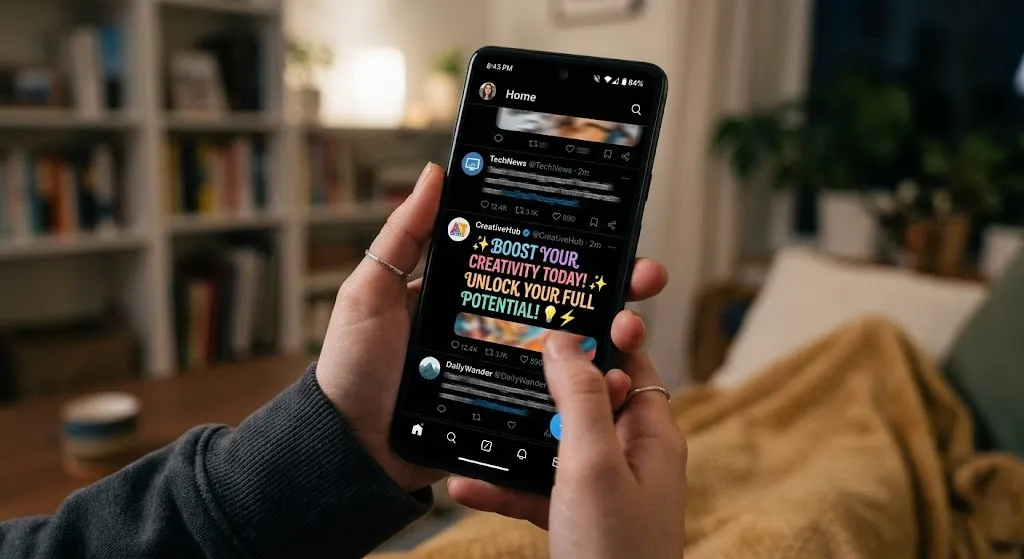
Warum Fancy Textstile auf Twitter/X wichtig sind
Fancy Textstile auf X (formerly Twitter) helfen dir, deine Tweets visuell hervorzuheben und mehr Aufmerksamkeit zu bekommen. In einem schnellen Feed machen kleine Unterschiede oft den größten Effekt.
Aufmerksamkeit & Scroll-Stop-Effekt
Im überfüllten Feed fallen stylische Texte sofort auf. Sie durchbrechen den normalen Textfluss und sorgen dafür, dass Nutzer beim Scrollen stoppen.
Engagement (Likes, Retweets, Replies)
Auffällige Texte machen deine Inhalte interessanter. Dadurch steigt die Wahrscheinlichkeit, dass Nutzer liken, kommentieren oder deinen Tweet teilen.
Persönliche Marke & Stil
Mit Fancy Text kannst du deinen eigenen Stil entwickeln. Das stärkt dein Branding und sorgt dafür, dass deine Tweets wiedererkannt werden.
Wie funktionieren Fancy Textstile technisch?
Fancy Textstile auf X (formerly Twitter) wirken wie besondere Schriftarten, sind aber technisch etwas anderes.
Unicode statt echte Fonts
Fancy Text ist keine echte Schriftart. Stattdessen werden normale Buchstaben durch Unicode-Zeichen ersetzt, die ähnlich aussehen (z. B. A → 𝓐, 𝔄, 🅰).
👉 Es handelt sich also um spezielle Symbole, nicht um Formatierung
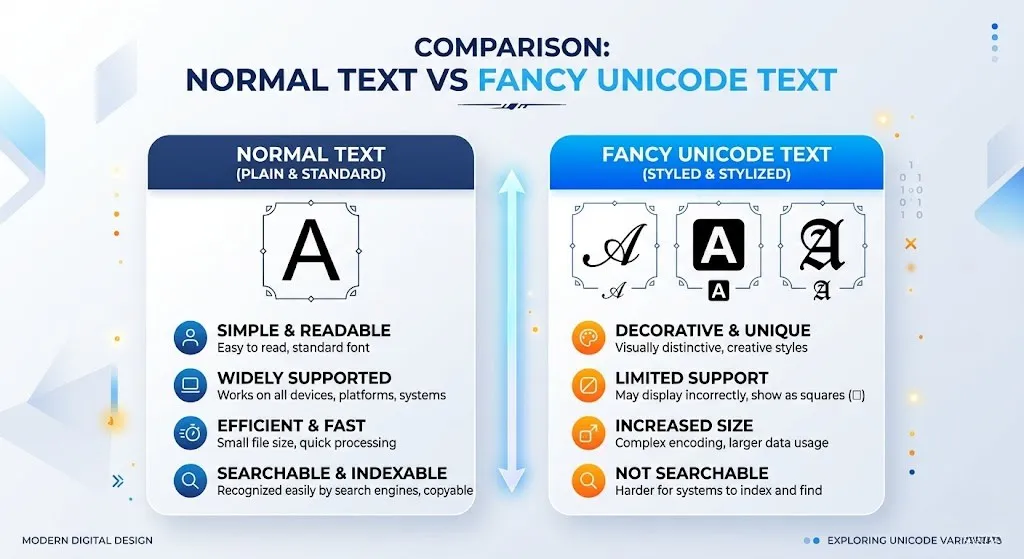
Copy & Paste Prinzip
Die Funktionsweise ist einfach:
- Text in einen Generator eingeben
- Stil auswählen
- Ergebnis kopieren
- In den Tweet einfügen
👉 Der Text bleibt „normaler Text“, nur mit anderen Zeichen
Darstellung auf verschiedenen Geräten
Unicode-Zeichen funktionieren auf den meisten Geräten (Android, iOS, Desktop).
Aber:
- Darstellung kann leicht variieren
- Manche Zeichen werden nicht überall gleich angezeigt
👉 Wichtig: Wähle einfache und gut lesbare Styles
Die besten Fancy Textstile für Twitter/X
Auf X (formerly Twitter) kannst du mit Fancy Textstilen deine Tweets optisch hervorheben und mehr Aufmerksamkeit gewinnen. Hier sind die beliebtesten Styles:
Fett & auffällige Schriftarten
Diese Stile sind perfekt, um wichtige Wörter hervorzuheben:
- 𝗙𝗮𝗻𝗰𝘆 𝗧𝗲𝘅𝘁
- 𝙁𝙖𝙣𝙘𝙮 𝙏𝙚𝙭𝙩
👉 Ideal für starke Hooks und Headlines
Kursiv & elegante Fonts
Diese wirken stilvoll und professionell:
- 𝘍𝘢𝘯𝘤𝘺 𝘛𝘦𝘹𝘵
- 𝒻𝒶𝓃𝒸𝓎 𝓉𝑒𝓍𝓉
👉 Perfekt für elegante und ruhige Inhalte
Kreative & dekorative Styles
Diese sind verspielt und besonders auffällig:
- 𝔉𝔞𝔫𝔠𝔶 𝔗𝔢𝔵𝔱
- 🅵🅰🅽🅲🆈 🆃🅴🆇🆃
👉 Gut für kreative und einzigartige Tweets
Wie man Fancy Text auf Twitter/X erstellt
Fancy Text auf X (formerly Twitter) wird mit speziellen Unicode-Zeichen erstellt. Da X keine eigenen Schriftarten anbietet, nutzt du dafür externe Tools.
Nutzung von Generatoren (z. B. LingoJam)
Mit Tools wie LingoJam oder Creative Fabrica kannst du deinen Text umwandeln:
- Text eingeben
- Stil auswählen (fett, kursiv, fancy)
- Ergebnis generieren
👉 Schnell und einfach verschiedene Styles testen
Copy & Paste Methode
Die einfachste Methode:
- Stylischen Text kopieren
- In deinen Tweet oder deine Bio einfügen
👉 Funktioniert direkt ohne zusätzliche Tools auf X
Kombination mit Emojis & Symbolen
Du kannst Fancy Text mit Emojis kombinieren:
- ✨ 𝗙𝗮𝗻𝗰𝘆 𝗧𝗲𝘅𝘁 ✨
- 🚀 𝘛𝘳𝘦𝘯𝘥𝘪𝘯𝘨 𝘕𝘰𝘸 🚀
👉 Macht deine Tweets noch auffälliger und ansprechender
Beispiele für Fancy Tweets
Auf X (formerly Twitter) funktionieren auffällige, kreative und emotionale Tweets am besten. Hier sind einige Beispiele:
Kurze auffällige Tweets
- ✨ 𝗘𝗶𝗻𝗳𝗮𝗰𝗵. 𝗞𝗹𝗮𝗿. 𝗦𝘁𝗮𝗿𝗸.
- 🚀 𝙉𝙚𝙭𝙩 𝙇𝙚𝙫𝙚𝙡.
- 💡 Weniger reden. Mehr machen.
👉 Kurz + visuell = mehr Aufmerksamkeit
Emotionale Hooks
- „Ich kann das nicht glauben… 😳“
- „Das wird dein Mindset verändern.“
- „Niemand spricht darüber, aber…“
👉 Neugier weckt mehr Engagement
CTA-basierte Tweets
- „Was denkst du darüber? 👇“
- „Welches Team bist du? 🔥 oder ❄️“
- „Markiere jemanden, der das sehen muss!“
👉 Fördert Kommentare & Interaktion
Häufige Fehler vermeiden
Auch auf X (formerly Twitter) können falsche Textstile deine Wirkung negativ beeinflussen. Vermeide diese typischen Fehler:
Konsistenter Stil
Bleibe bei einem einheitlichen Schreibstil und Design. So erkennen Nutzer deine Tweets schneller wieder.
Fazit
Auf X (formerly Twitter) kommt es auf die richtige Balance an. Kreative Textstile können Aufmerksamkeit bringen, sollten aber immer gut lesbar bleiben.
Setze auf einen klaren, konsistenten Stil, der deine Persönlichkeit oder Marke widerspiegelt. So wirken deine Tweets nicht nur auffällig, sondern auch professionell.